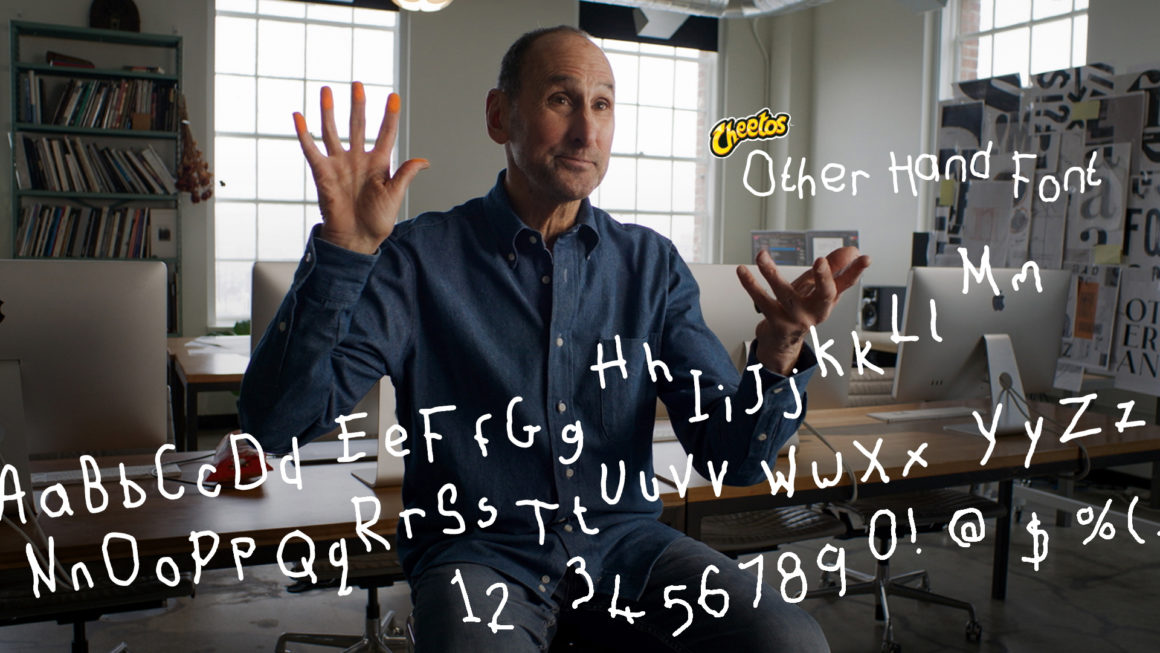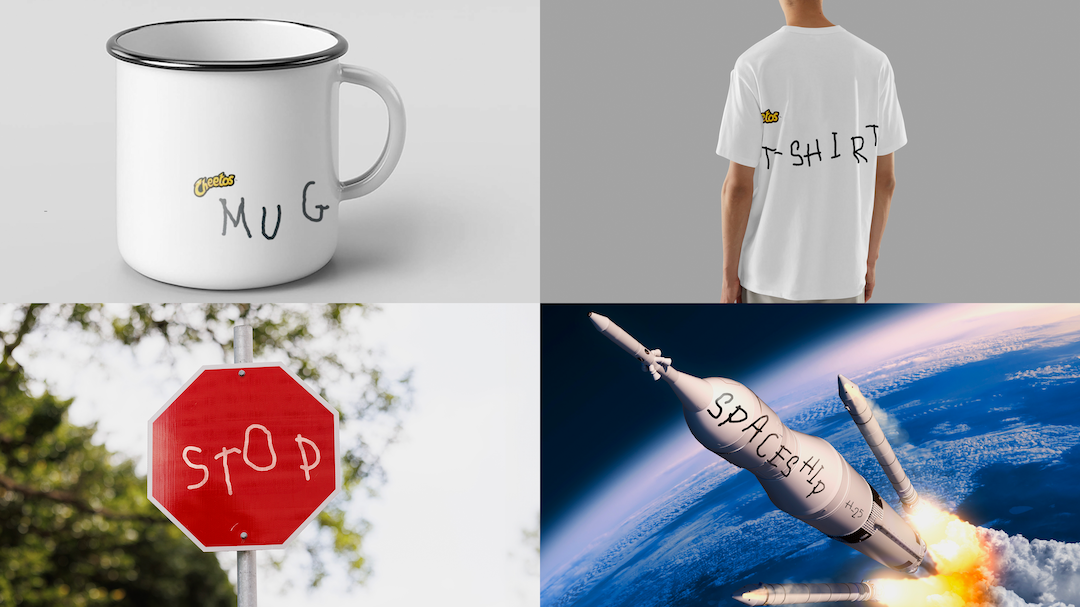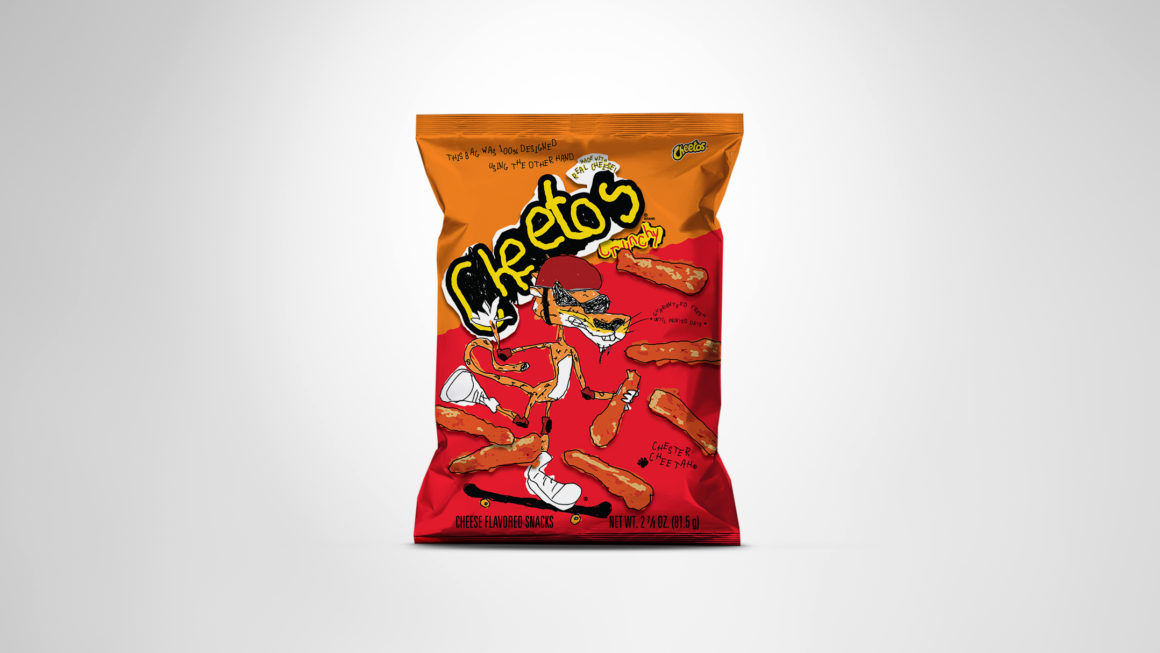
Cheetos lance une typographie… écrite avec la mauvaise main !
Si vous pensiez que Cheetos ne pouvait pas aller plus loin dans l’art de célébrer les doigts orange, détrompez-vous.
La célèbre marque de snacks revient avec une innovation aussi décalée qu’amusante : The Other Hand Font, une police de caractères entièrement dessinée… avec la main non dominante. Une idée qui s’inscrit dans leur campagne Other Hand, mettant en avant la façon dont les fans de Cheetos utilisent leur main libre pour vivre leur vie, l’autre étant bien évidemment recouverte de Cheetle, cette poudre orange emblématique.
Une idée aussi brillante que déjantée
Imaginée par Goodby Silverstein & Partners, l’agence derrière les campagnes les plus mémorables de Cheetos, cette police de caractères se veut un hommage à l’art de grignoter… et aux petites maladresses qui en découlent. Rich Silverstein, cofondateur de l’agence et légende de la publicité, a travaillé main dans la main (sans mauvais jeu de mots) avec les designers de Silverstein Goodby & Partners pour créer une police qui reflète l’esprit espiègle de Cheetos.
“Le design est la forme d’expression la plus pure d’une marque, et cette police incarne parfaitement l’identité de Cheetos. Créer chaque lettre avec notre main non dominante a été une expérience hilarante qu’on n’oubliera pas de sitôt”, explique Silverstein.
Quand les snacks inspirent le design
The Other Hand Font n’est pas qu’une blague. Elle symbolise la nature décomplexée et ludique des fans de Cheetos. Que vous soyez en train d’écrire un email, de rédiger une présentation ou même de signer un contrat (soyons fous), cette police est là pour vous rappeler que parfois, il faut savoir lâcher prise… ou sa main dominante.
Un concours pour les esprits les plus créatifs
“Ce qu’il y a de génial avec la campagne ‘Other Hand’, c’est qu’elle met en lumière une vérité humaine simple : la plupart des gens utilisent leur main dominante pour manger des Cheetos, ce qui les oblige à tout faire d’autre avec leur autre main. Cette nouvelle police est une manière hilarante de célébrer ce désordre espiègle,” explique Chris Bellinger, directeur créatif chez PepsiCo Foods US.
Une approche ludique du branding
Cheetos ne s’est jamais contenté de vendre des snacks ; la marque a toujours cherché à intégrer un côté ludique et interactif à ses campagnes. Avec The Other Hand Font, elle montre une fois de plus qu’un branding réussi peut être créatif, surprenant et engageant. En jouant avec une idée aussi simple que l’utilisation de la mauvaise main, Cheetos rappelle que l’essence de la marque est dans le fun, l’inattendu… et un peu de désordre.
Conclusion : une police qui a du mordant
The Other Hand Font est bien plus qu’une simple police de caractères. C’est une expérience créative, un clin d’œil espiègle à la culture du snacking et une invitation à ne pas se prendre trop au sérieux. Alors, que ce soit pour rédiger une carte d’anniversaire ou pour signer un document important (à vos risques et périls), cette nouvelle police vous invite à voir les choses sous un angle… légèrement tordu. Après tout, pourquoi se contenter d’Helvetica quand on peut écrire avec un peu de Cheetle ?